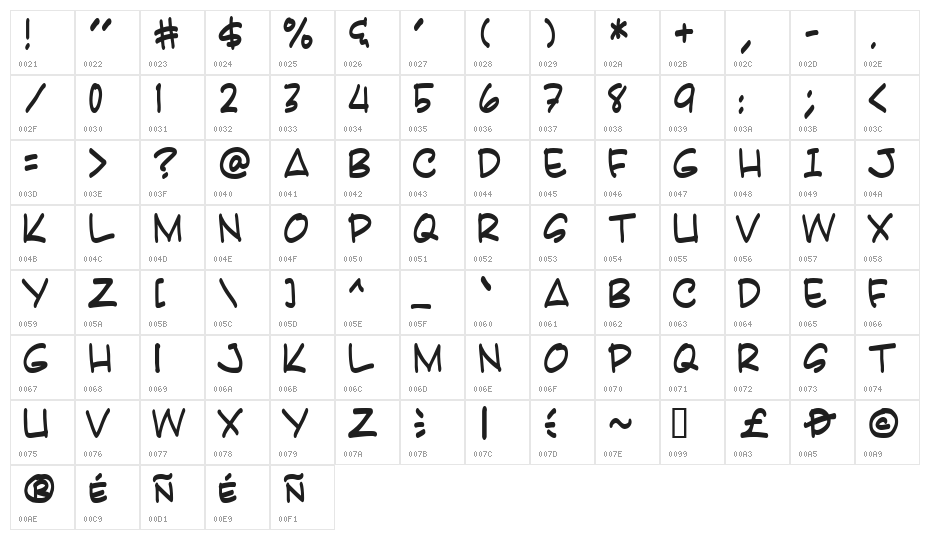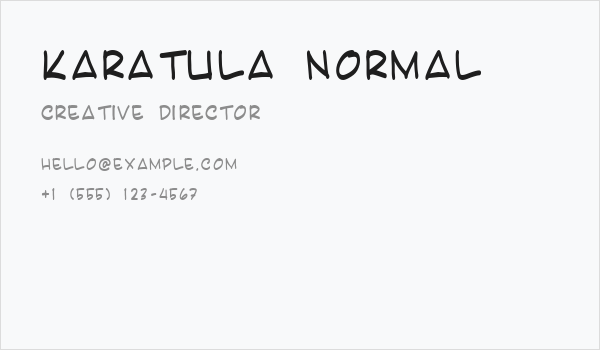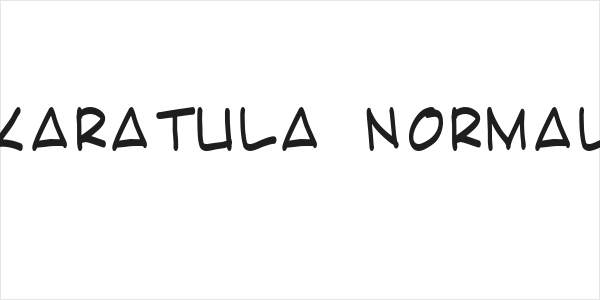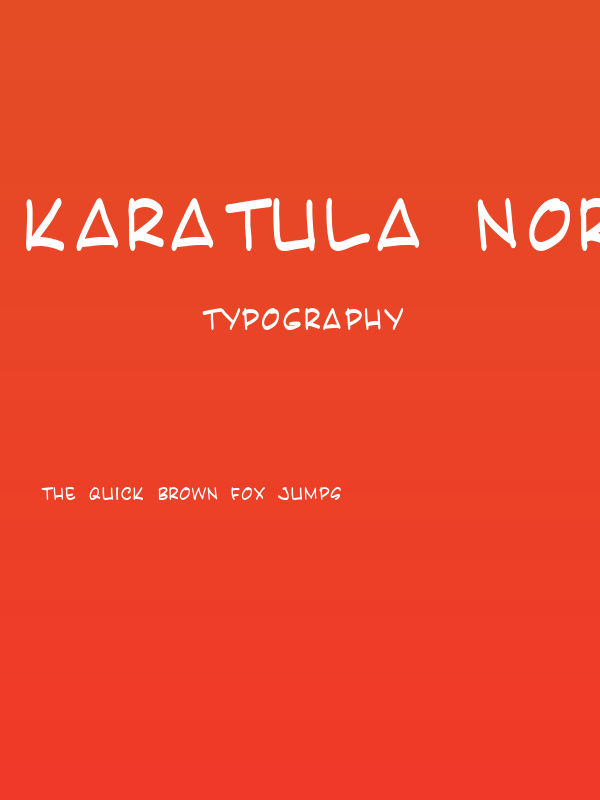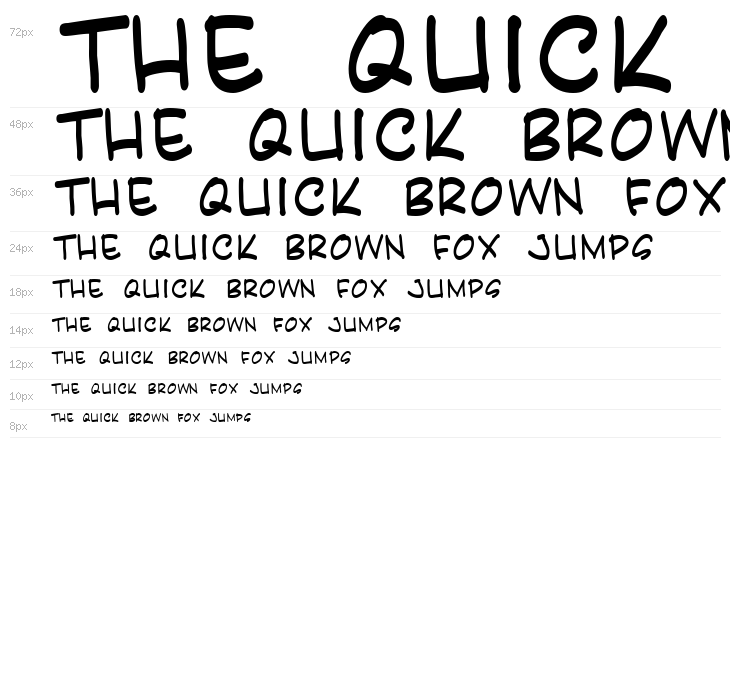
Karatula Normal Font
| Gesamtstil | Casual |
| Anwendungsfall | Headlines, Informal text, Creative projects |
| Vorgeschlagene Projekte | Ideal for greeting cards, children's books, casual branding, and creative posters. |